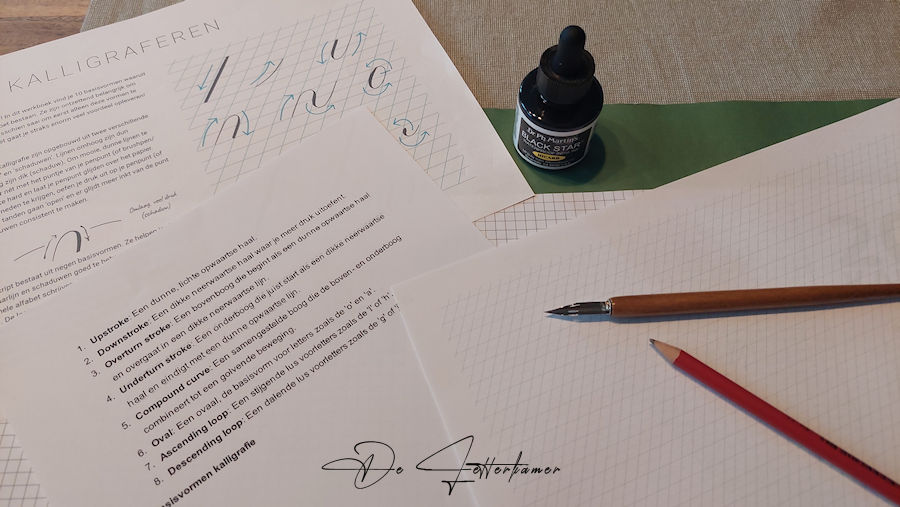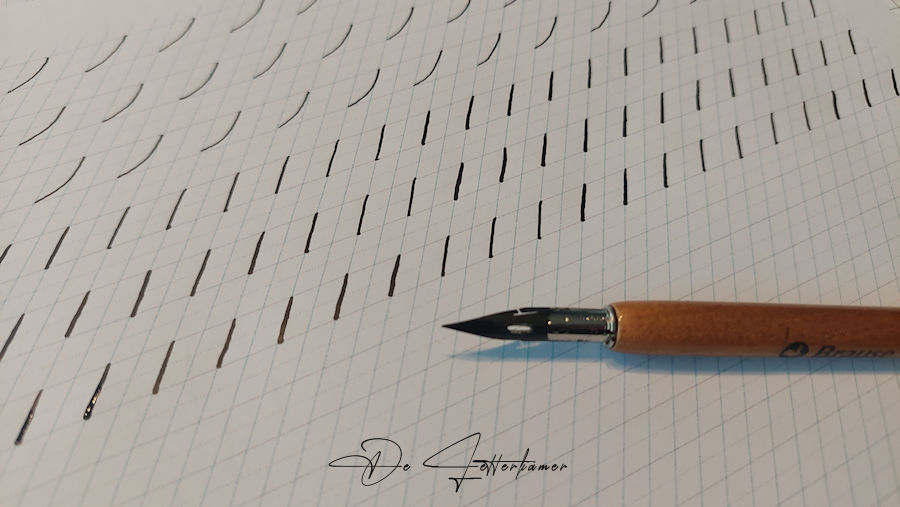
Even aan de kant, het pakje is gearriveerd!
De rechte en olique penhouder, de nibs, en de inkt.
Voor de nibs heb ik voor Nikko G gekozen, de andere die ik wou Zebra G die waren er niet. Beiden zijn aanbevolen om mee te starten. Ik volg het advies van Rosanne op, dan kan het niet fout lopen. Een Nederlandse site, met heel wat informatie op. Een aanrader!
We zijn er klaar voor, en met de rechte penhouder.
Eerst heb ik de nib met zeep de vetlaag verwijderd, er blijkt een vetlaagje op te zitten volgens kenners, die hebben we eerst verwijderd, zodat deze goed de inkt opneemt. En we zijn vertrokken nadat ik mijn hand heb opgewarmd, dit is echt wel noodzakelijk. Tot mijn grote verbazing, ging het goed. Beter dan verwacht, eigenlijk vind ik de penhouder gemakkelijker dan de brushpen. De druk die ik telkens moet aanpassen gaat vlotter, juist de consistentie die moet nog veel beter. Gelijk is het nog steeds niet. 2 pagina’s heb ik nu geoefend, de rest is voor de volgende keer.
Hier heb ik de eenvoudige basisvormen geoefend. De upstroke en de downstroke. Maar daarover meer in mijn volgende blog!